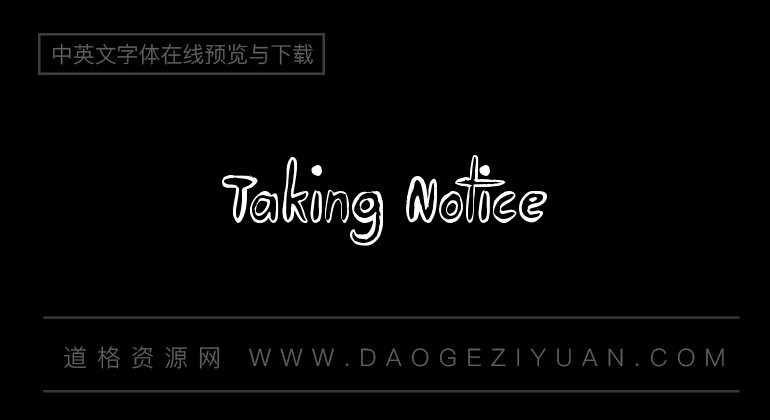
Taking Notice
Taking Notice 是一款由 Typodermic Fonts 公司设计的非常优雅的字体。它的特点是细节丰富,笔画精细,体现出精致的设计感,可以用于各种海报、标志、封面等设计中,也可以用于网页设计。它的字形具有良好的可读性,可以清晰地表达文字信息,更能增强文字的视觉效果,让设计师们更容易创作出更具有吸引力的作品。
Taking Notice是一款非常不错的手写艺术字体,具有很好的视觉感,适合于文化类的宣传设计、商业类品牌的广告和产品包装设计以及个性化文字排版等较多场景。